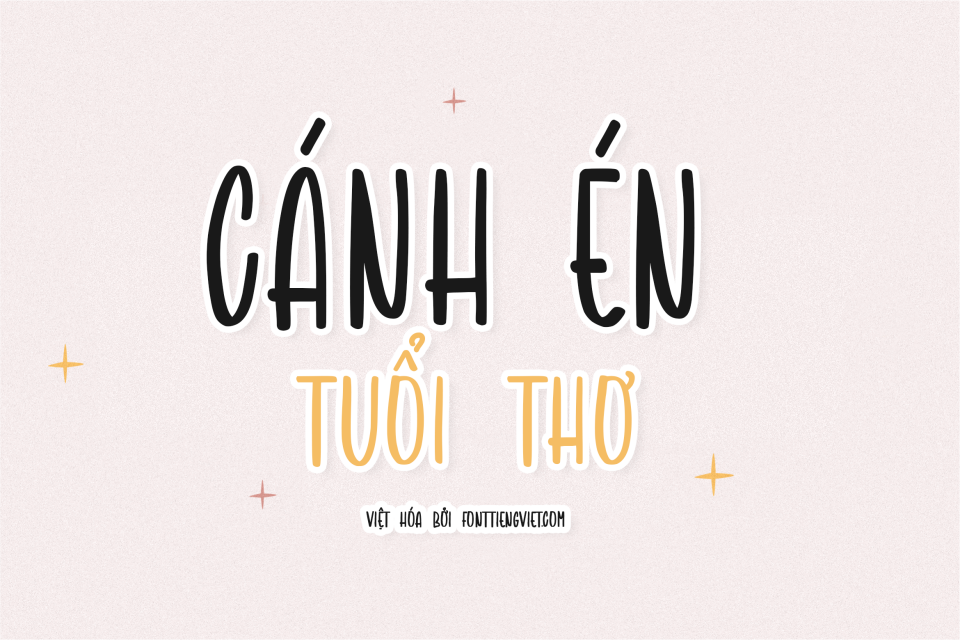
Font việt hóa 1FTV Nightheart
Giới thiệu về Font việt hóa 1FTV Nightheart
Trong thế giới thiết kế đồ họa, việc lựa chọn một Font Miễn Phí chất lượng luôn là ưu tiên hàng đầu của các bạn học sinh và thầy cô giáo khi làm bài thuyết trình hay báo tường. Font việt hóa 1FTV Nightheart nổi lên như một hiện tượng nhờ phong cách Brush đầy cá tính, mạnh mẽ nhưng không kém phần uyển chuyển. Đây là bộ phông chữ được tinh chỉnh kỹ lưỡng về dấu tiếng Việt, giúp người dùng không còn lo lắng về lỗi hiển thị khi soạn thảo nội dung. Với đường nét mô phỏng nét vẽ tay tự nhiên, bộ font này mang đến hơi thở hiện đại và sự phá cách cho mọi tác phẩm nghệ thuật.
Ưu điểm nổi bật của Font việt hóa 1FTV Nightheart
Phong cách thiết kế độc đáo
Font việt hóa 1FTV Nightheart sở hữu những nét vẽ thô mộc, tạo cảm giác gần gũi và chân thực. Sự kết hợp giữa các nét thanh nét đậm không đồng nhất giúp tạo điểm nhấn thị giác cực mạnh, rất phù hợp để làm tiêu đề cho các dự án sáng tạo. Những ký tự được chăm chút tỉ mỉ, đảm bảo tính thẩm mỹ cao trên cả màn hình kỹ thuật số và bản in thực tế.
Tính ứng dụng linh hoạt trong học tập
Bộ font này không chỉ dành cho các nhà thiết kế chuyên nghiệp mà còn cực kỳ hữu ích trong môi trường học đường. Các bạn học sinh có thể dùng nó để trang trí bìa tiểu luận, làm thiệp chúc mừng thầy cô hoặc thiết kế áo lớp. Sự linh hoạt của nó giúp mọi ý tưởng trở nên sinh động và chuyên nghiệp hơn bao giờ hết.
Cách sử dụng và kết luận
Để đạt hiệu quả tốt nhất, bạn nên kết hợp bộ font này với các phông chữ không chân (Sans-serif) đơn giản nhằm tạo sự cân bằng cho bố cục. Font việt hóa 1FTV Nightheart chính là lựa chọn hoàn hảo để nâng tầm thương hiệu cá nhân của bạn. Đừng quên ghé thăm trang web Font Miễn Phí, Font Việt Hóa, Font việt hóa 1FTV Nightheart thường xuyên để cập nhật thêm nhiều tài nguyên hữu ích. Hy vọng bộ font này sẽ trở thành người bạn đồng hành đắc lực trong hành trình sáng tạo của bạn.